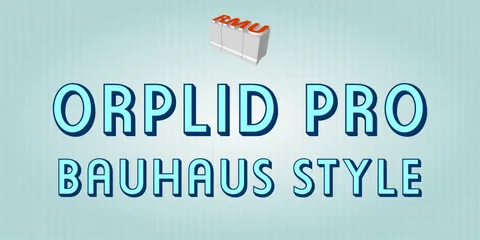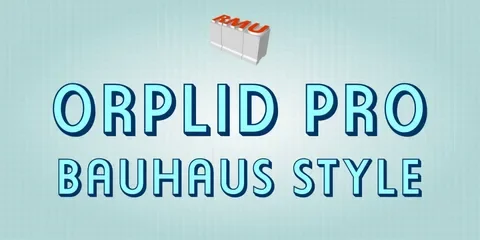
Название: Orplid Pro Font (2021)
Orplid Ганса Бона, теневой шрифт без засечек, созданный под сильным влиянием господствовавшего в то время стиля Баухаус и выпущенный компанией Klingspor в 1929 году, был возрожден и значительно расширен для многоязычного использования. Кроме того, был создан стиль заливки, позволяющий легко создавать красочные заголовки, объявления и плакаты.
Оба стиля имеют альтернативные варианты для A, M, N и W.